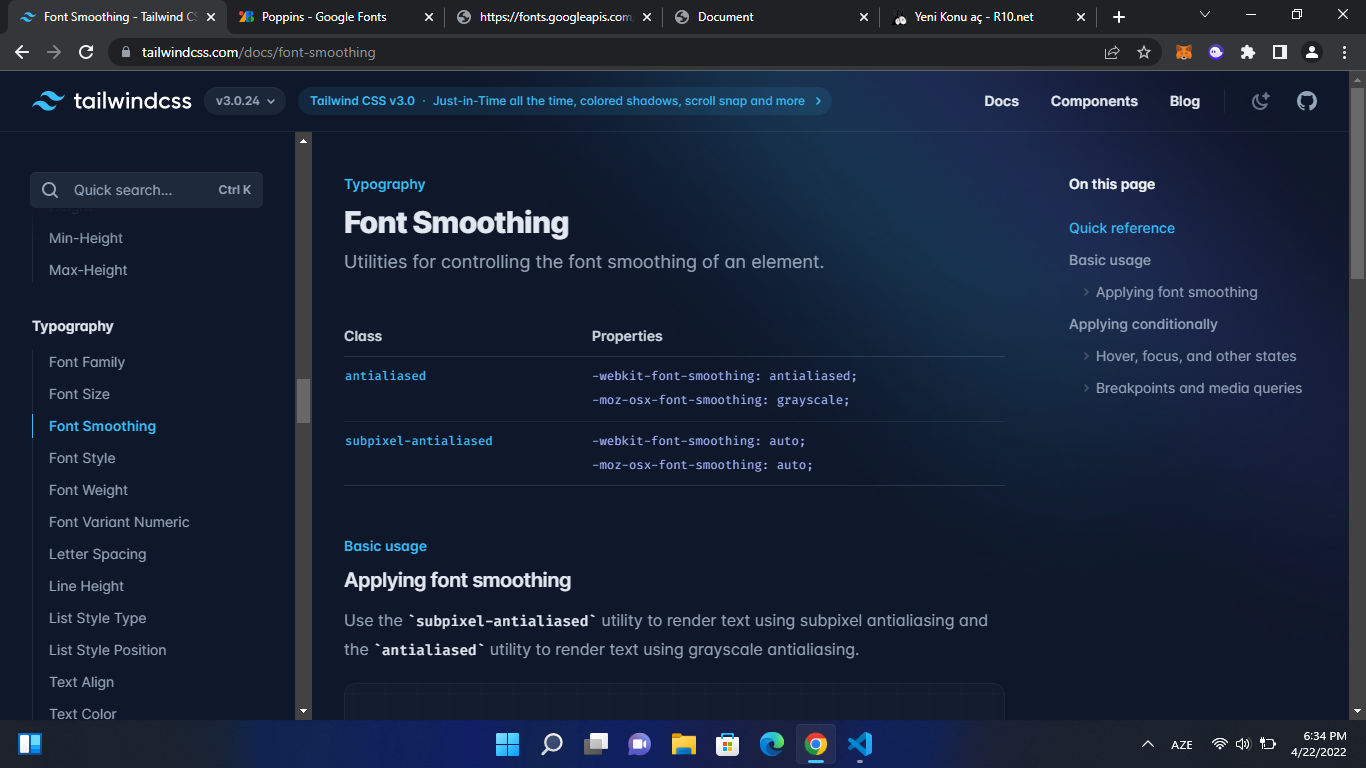
Merhaba. Prototürk kanalında Tayfun Erbilen'in ReactJS ile yaptığı bir projede Tailwind CSS'in bir özelliği olan antialiased özelliğini kullandığını gördüm. Bu özellik sanırım fontları özel yapıda, daha farklı yapıda gösteriyor gibi geliyor bana sayfada bildiğim kadarıyla. Tam emin değilim açıkçası ben bu özelliği ilk defadır duyuyorum. Bilgisi olan var mı bu konuda? Örnek vermek gerekirse, ben mesela her türlü güzel fontları denedim sayfamda fakat güzel gözükmüyor. Lakin şu sayfaya bakar mısınız ne kadar güzel gözüküyorlar değil mi?
Bu ya da bunun gibi farklı web sayfalarında baktım ve inceledim. Çok güzel gözüküyor fontlar. Ben ekliyorum mesela hiç hoşuma gitmiyor. Özel bir kod yazılıyor kesin bunun için.